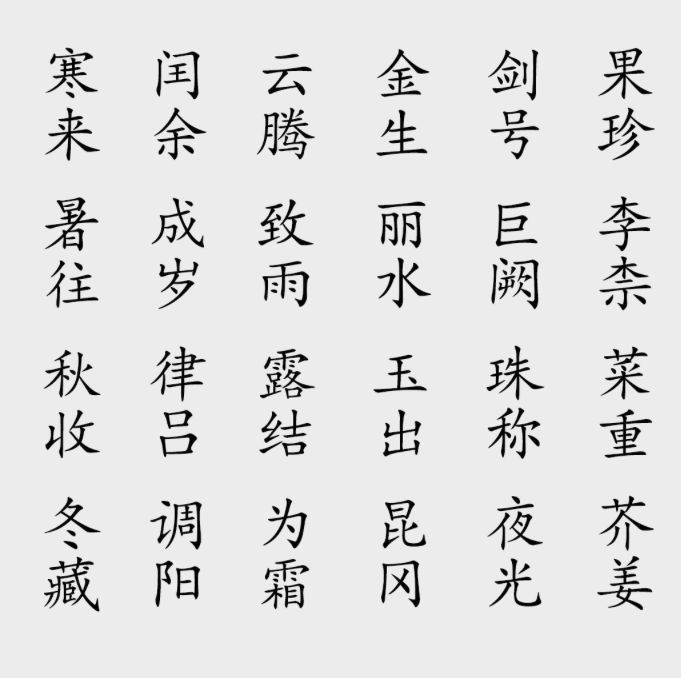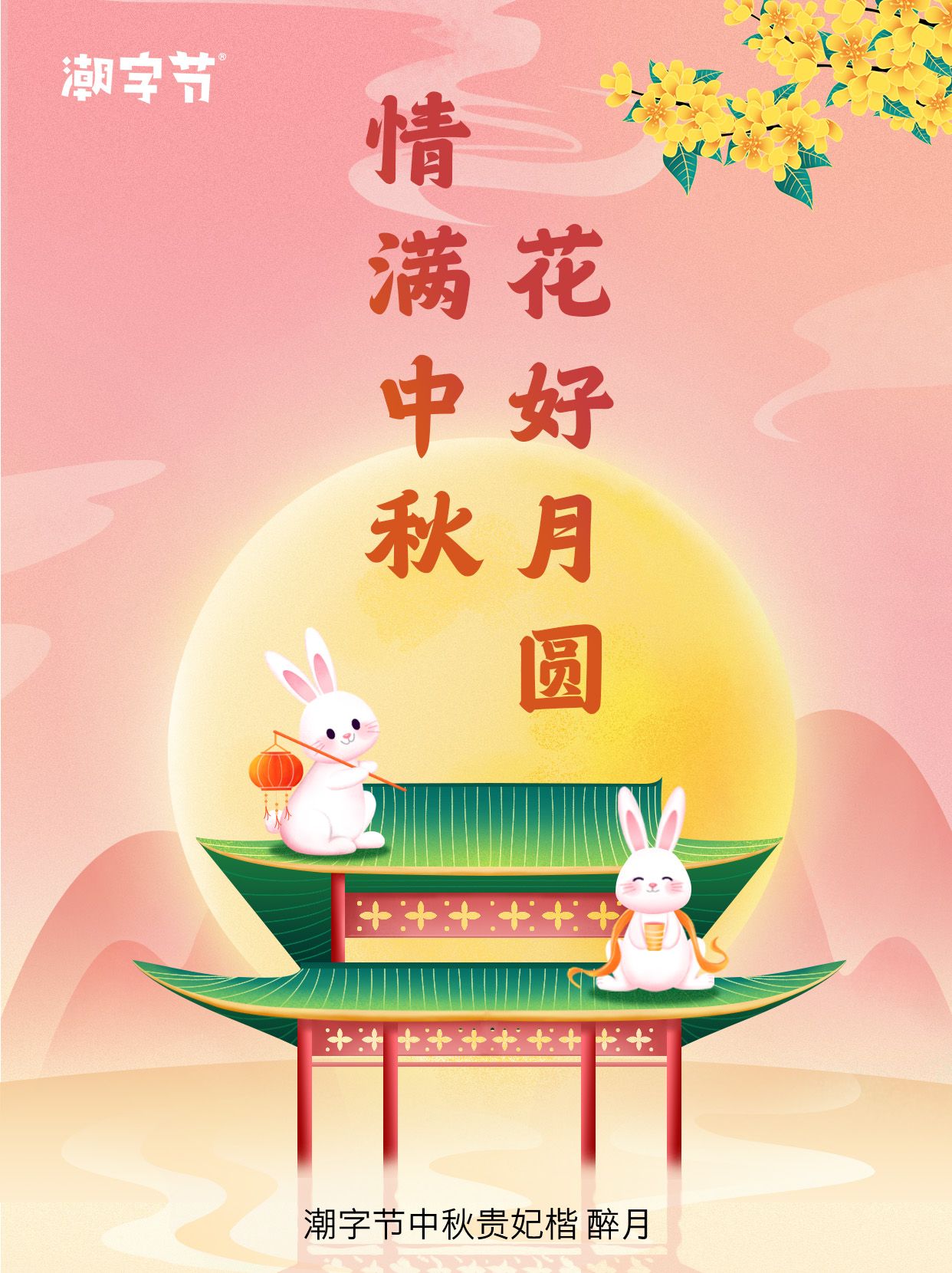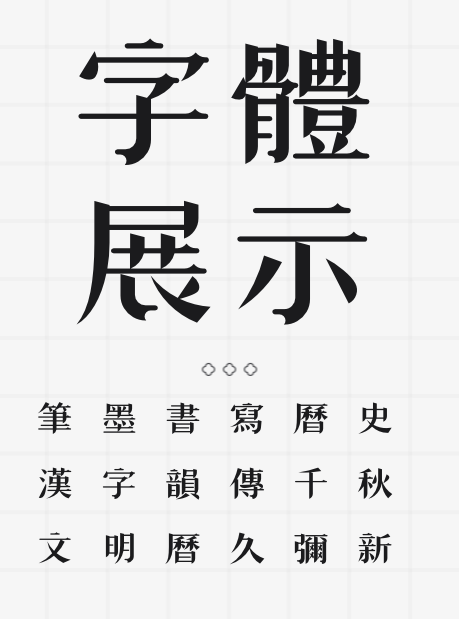
言情剧字幕优选:三款真实字体,演绎浪漫篇章
在言情剧的细腻情感中,字幕的选择同样至关重要。一款合适的字体,能够精准传达剧中人物的情感波动,让观众在视觉与文字的交织中,沉浸于浪漫的故事世界。今天,就让我们一同探索三款真实存在的、专为言情剧设计的字体产品,它们将如何以独特的韵味,演绎言情剧的浪漫篇章。
1. 汉字之美楷体
汉字之美楷体以其简约而不失优雅的线条,成为言情剧字幕的优选之一。这款字体笔画清晰,结构匀称,既能够准确传达台词内容,又能够在视觉上营造出一种清新脱俗的氛围。在展现剧中人物间的甜蜜互动时,汉字之美楷体能够以一种低调而内敛的方式,传递出那份细腻的情感。
2. 潮字节中秋贵妃楷 醉月
潮字节中秋贵妃楷则以其流畅自然的笔触和独特的字形设计,为言情剧增添了一抹艺术气息。这款字体笔画间充满韵律感,仿佛能够随着剧情的起伏而舞动。在展现主角间的深情告白或重要情感转折时,潮字节中秋贵妃楷能够以一种生动而富有感染力的方式,将观众带入剧情的深处,感受那份真挚的情感。
3. 潮字社国风冉宋简繁
潮字社国风冉宋简繁以其细腻而富有女性化的设计,成为言情剧中女性角色台词的绝佳选择。这款字体笔画柔和,字形优美,仿佛能够勾勒出女性角色的温婉与柔情。在展现女性角色内心的情感波动时,潮字社国风冉宋简繁能够以一种细腻而温柔的方式,将观众带入角色的内心世界,感受那份细腻而真挚的情感。
三款字体各具特色,它们以独特的韵味和风格,为言情剧的字幕设计提供了丰富的选择。在言情剧的浪漫篇章中,这些字体将如何演绎出一个个动人的故事,让我们拭目以待。